Top 5 font Việt hóa chữ tròn mập mạp ngộ nghĩnh
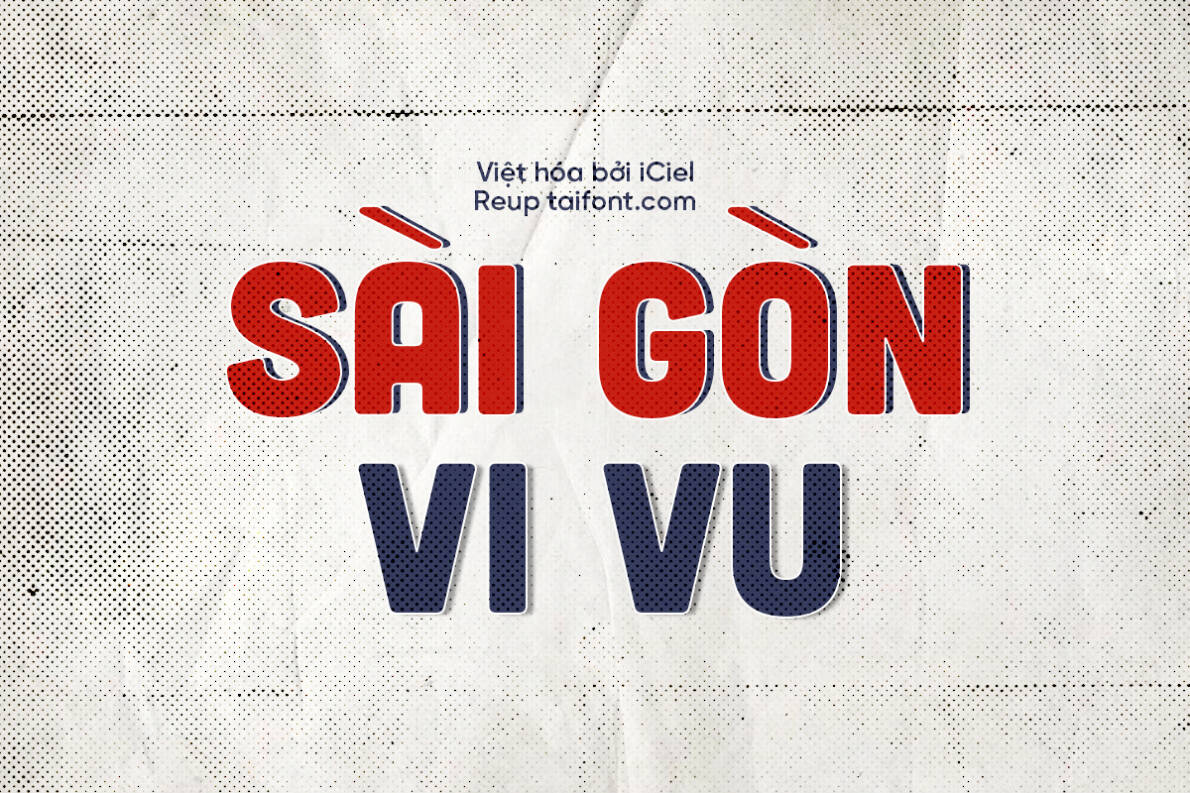
Top 5 font Việt hóa chữ tròn mập mạp ngộ nghĩnh, đây là những font chữ sẽ phù hợp với những thiết kế cần sự dễ thương, làm tiêu đề.
Top 1: Font Việt hóa TF Mayura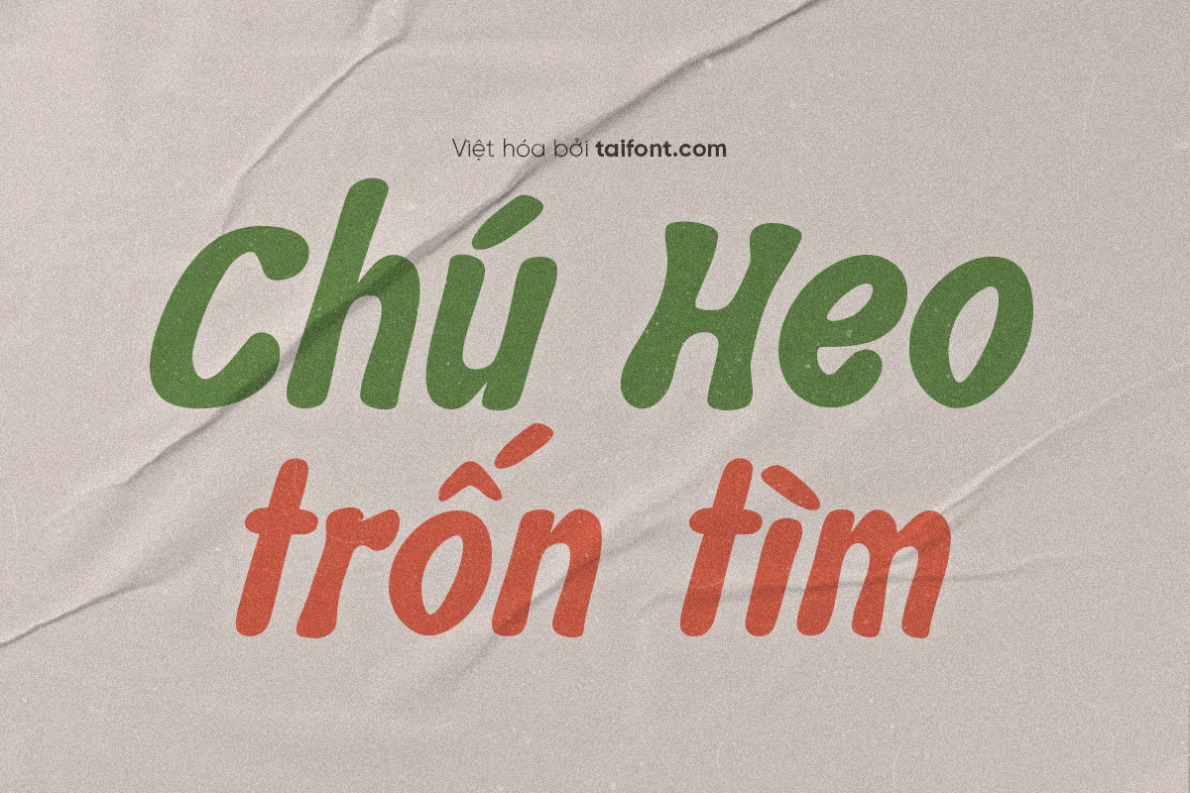
Font Việt hóa TF Mayura có nét béo tròn, font phù hợp với thiết kế ẩm thực hoặc thiết kế liên quan tới trẻ em.
Top 2: Font Việt hóa UTM 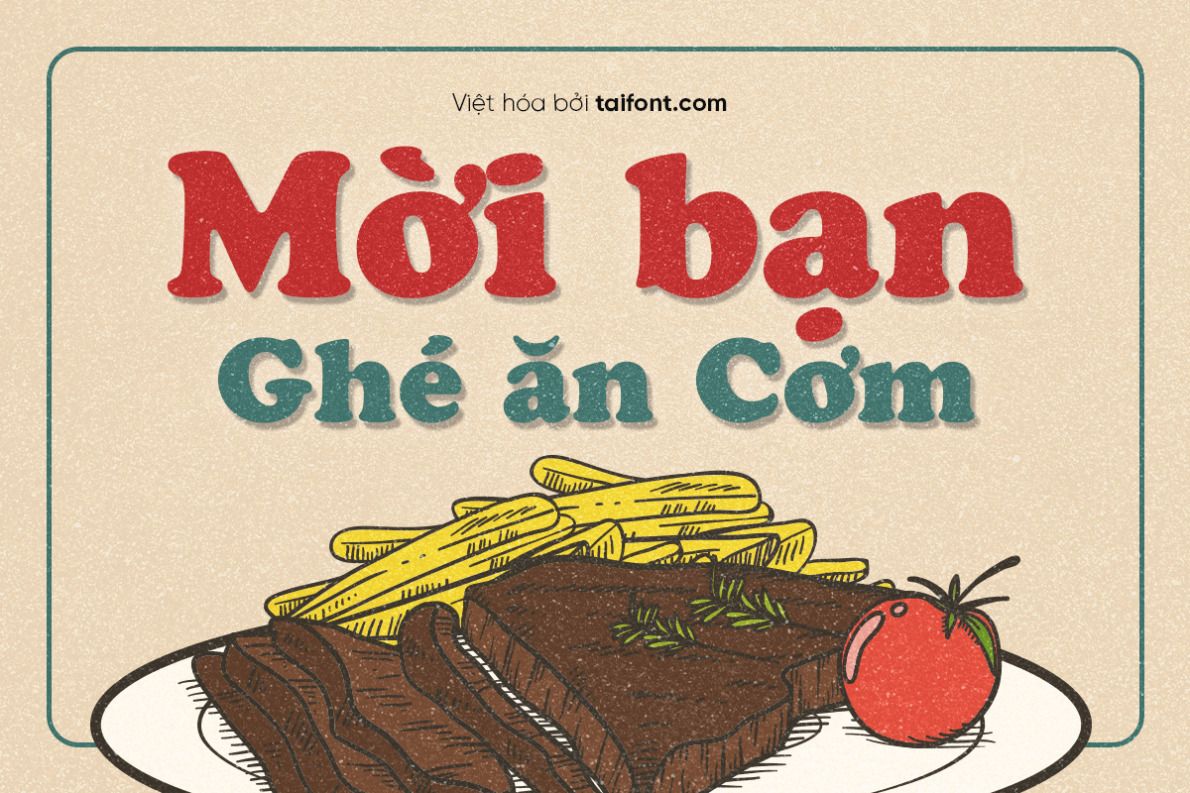
Font Việt hóa UTM Cooper là một font chữ kinh điển được sử dụng rất nhiều tại Việt Nam.
Bạn có thể nhìn thấy font Cooper trong các bảng cáo cáo quán ăn nhất là các quán cơm.
Top 3: Font Việt hóa Bungee Regular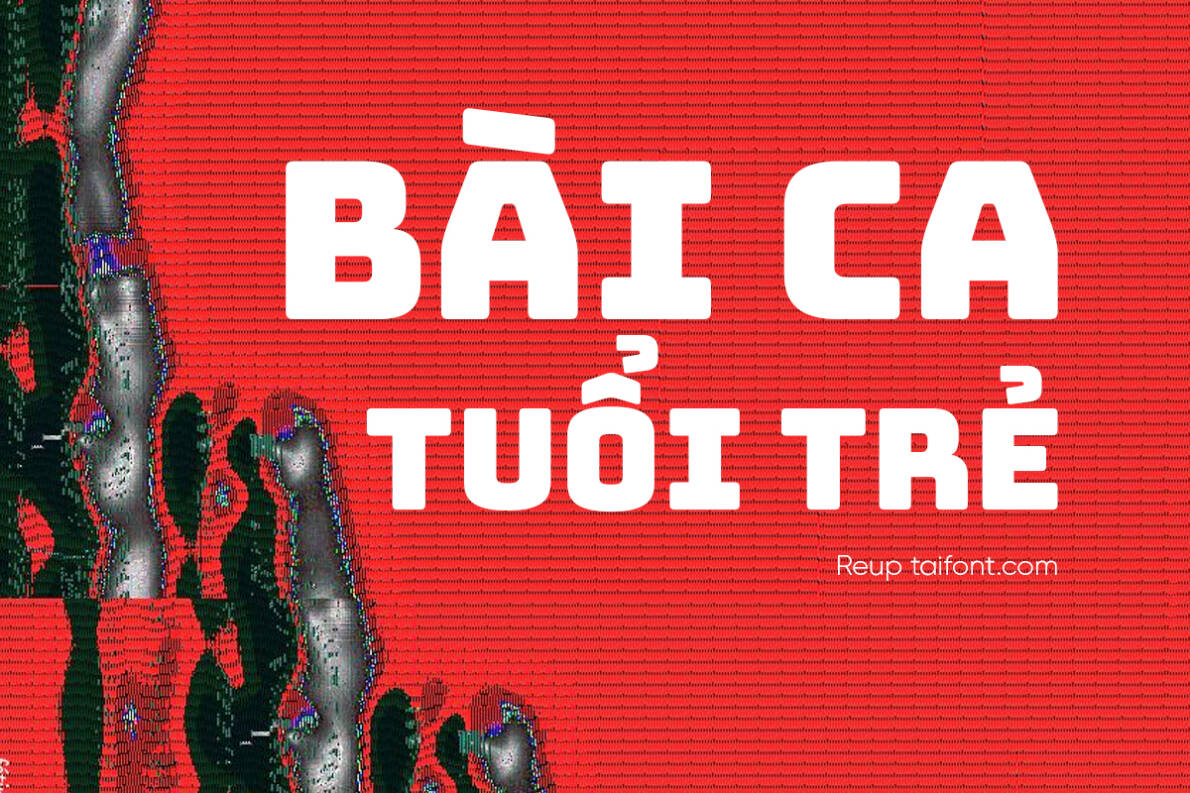
Font Việt hóa Bungee là một font chữ được chia sẻ trên Google font. Font có nét đậm và chắc chắn.
Đối với font chữ Bungee bạn có thể dùng nó để thiết kế các biển quảng cáo, biển báo thông tin. Với đường nét đậm có thể quan sát thấy nội dung từ xa.
Font do tác giả David Jonathan Ross và thuộc nhóm font Trang trí.
Top 4: Font Việt hóa iCielBC
Font Việt hóa iCielBC Cubano là một font chữ được yêu thích sử dụng tại Việt Nam bởi nét đẹp của nó.
Cubano thuộc dạng font Vintage, không chân có đặc điểm nét đậm. Font phù hợp đang dạng sử dụng trong thiết kế quảng cáo, slide thuyết trình.
Font Cubano được dùng rất nhiều trong thiết kế ấn phẩm truyền thông.
Việt hóa bởi font iCiel
Top 5: Font Việt hóa TF Cafillen